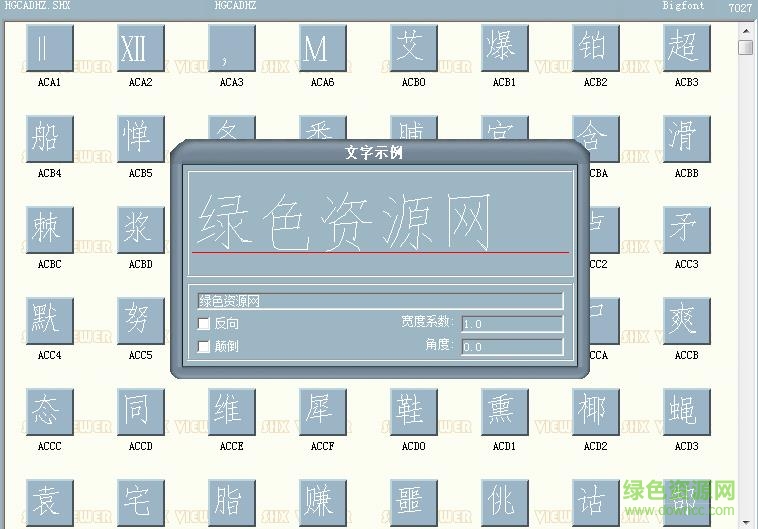
hgcadhz.shx字體的運(yùn)用效果十分不錯(cuò),在制圖中提供你清晰的顯示效果,更有快速的輸入體驗(yàn),滿足你的眾多制圖需求,能夠快速打出你所需要的字體樣式!
hgcadhz.shx將讓你感受到不同一般字體的顯示效果,它的行文風(fēng)格十分獨(dú)特,在使用中不僅能夠完成繪制的需求,還能夠提供用戶看圖的最佳體驗(yàn)!